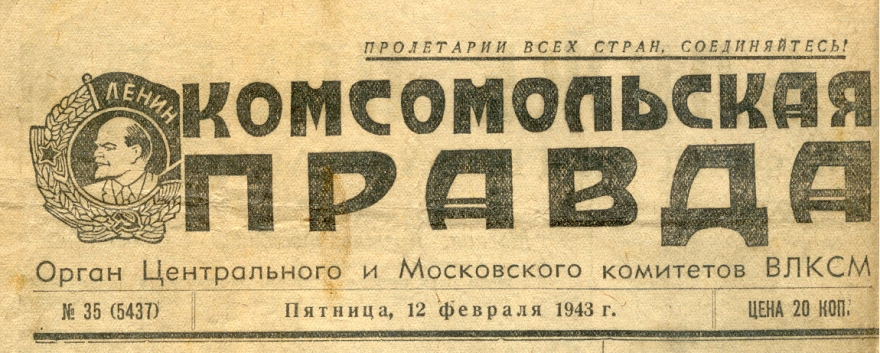
от элемента к системе. анализ шрифтового расписания одной из газет (журнала) [Курсовая №35505]
Введение
Газета является периодическим изданием, которое люди зачастую читают на ходу или транспорте, поэтому для газетных шрифтов немаловажна удобочитаемость текста даже в мелких кеглях, в связи с чем снискали популярность шрифты с широким четким буквенным очком. В современной печати также имеется тенденция к уменьшению кегля, так как редакции стараются уместить максимум информации на ограниченной площади. На данный момент в газетах используется набор текста 8-9 кеглем, но встречаются и издания, практикующие набор 6-7 кеглем. Для подтверждения упомянутой тенденции к уменьшению не могу не привести в пример издания периода окончания Октябрьской революции, набор текста которых производился весьма крупным, по современным меркам, 12-14 кеглем. В те времена данный размер шрифта был оправдан значительной малограмотностью населения, а также банальным отсутствием навыков чтения периодических изданий, ведь в это время в России подобный формат изданий только набирал обороты.
С течением времени газеты видоизменялись в шрифтовом оформлении благодаря повышению грамотности населения, а также увеличению потока информации, необходимой уместить на ограниченном пространстве, тем самым уменьшение шрифта было обосновано, однако приходилось работать над его удобочитаемостью с уменьшением кегля.
Несмотря на то, что современным миром правит интернет, вытесняющий газеты и телевидение, газеты остаются популярным новостным ресурсом, все так же востребованным со стороны большей части населения. Как показывает статистика, чтением газет на регулярной основе в России и странах СНГ занимаются люди от 25 лет и старше, что является весомой аудиторией, поэтому периодические издания продолжают развиваться и выпускаться в больших тиражах.
В своей работе я рассмотрю историю российских периодически изданий, шрифтовые изменения в них, их причины и следствия, особенности российских шрифтов и современный их вид. Предметом моего изучения выступит сам шрифт, применяемый в газетах, в то время как объектом исследования послужат примеры и особенности применения текстовых и заголовочных шрифтов в оформлении газет.
В газетах шрифты используются для оформления заголовков, набора основного текста и его выделения. В связи с выполнением этих функций шрифты подразделяются на заголовочные, текстовые и выделительные. В некоторых случаях один и тот же шрифт может выполнять несколько функций сразу. Газетные шрифты-это шрифты, как правило, прямые светлого начертания, однако крупные издания современного мира все чаще используют фирменные шрифты для набора текста. Использование фирменного шрифта значительно поднимает престижность издания. Допускаются разные варианты шрифтового оформления – набор текста с использованием нескольких различных гарнитур или набор всего теста одной гарнитурой и ее различными начертаниями. Абсолютное большинство изданий использует набор в несколько различных гарнитур, одна из которых используется в качестве текстовой, а остальные играют роль заголовочных и выделительных.
Данный способ набора текста разительно облегчает выделение текста и позволяет не заскучать читателю из-за разнообразного оформления текста. В случае же использования лишь одной гарнитуры эффект выделения достигается путем изменения кегля и его начертания, но гарнитура остается неизменной.
Чем более высока значимость статьи, тем более крупный кегль для ее набора используется. Изменение кегля шрифта активно применяется для смыслового выделения частей текста и расставления в нем акцентов. К примеру, для того чтобы обратить читательское внимание на важность статьи, первый ее абзац набирают заметно более крупным кеглем нежели основной текст.
1.2 Шрифтовые средства выделения текстаПри необходимости выделения определенного отрывка текста или слова в газетах применяются шрифты той же гарнитуры что и основной текст, только прямые полужирные и светлые курсивные, в отличии от светлого прямого начертания основного текста. Курсив, в отличии от полужирного, заметно хуже воспринимается человеческим глазом.
Полужирное начертание дает сильное выделение текста.
Шрифтовой отбор для периодического издания невероятно суров, так как мало в какой еще области типографики шрифтовая гарнитура должна отвечать множеству требований сразу. Газетный шрифт должен быть хорошо виден как на плохой, так и промышленной бумаге высоко касса, разборчив, удобочитаем, а также компактен. На протяжении последнего века велась активная разработка шрифтов отвечающих множеству требований печати периодических изданий. Необходимо отметить что разработка завершилась успехом, ведь именно за последнюю сотню лет и были созданы наиболее успешные и узнаваемые газетные шрифты. К примеру, Times New Roman, разработанный для одного из крупнейших издательств «The Times». Несмотря на то, что Times New Roman был признан едва ли не по всему миру, в современности его используют везде кроме газетных издательств. Исключения составляют лишь мелкие еженедельные или ежемесячные издания.
Что иронично, даже сами «The Times» отказались от использования Times New Roman еще пару десятилетий назад, разработав серию собственных шрифтов.
На данный момент также ведется активная разработка газетных шрифтов, обоснованная изобретением все новых и новых способов печати. Однако нашли применение, так сказать, «устаревшим» шрифтам. Компания Mergenthaler Linotype была ответственна за изготовление ряда шрифтов, подходящих для создания дизайна газет и журналов, в период 30-40 годов прошлого века. Некоторые из этих шрифтов перевели в цифровой формат, что позволяет пользоваться «устаревшими» шрифтами и в 21-ом веке. Многие шрифты сейчас имеют и свое цифровое воплощение, чему обязаны не стоящему на месте прогрессу и изобретению офсетной печати. Перевод шрифта в цифровой формат позволяет адаптировать его в краткие сроки и приспособиться к новым видам печати.
1.4 Шрифтовые градации«Современные шрифты», с начала широкого распространения газет среди населения еще с начала 19 века, прочно заняли доминирующую позицию в периодических изданиях, поэтому многим из хорошо знакомых читателям шрифтов сейчас возвращают первоначальный вид.
Шрифт Matthew Carter’s Miller, основывающийся на Scotch Roman является ярким примером данного явления. Сказать, что Carter копирует своего предшественника нельзя, однако отзывы критиков говорят о том, что возвращение к истокам пошло шрифту на пользу. На сегодняшний день Miller активно используется в таких журналах как Newsweek, а также была сделана его адаптация для «The Guardian».